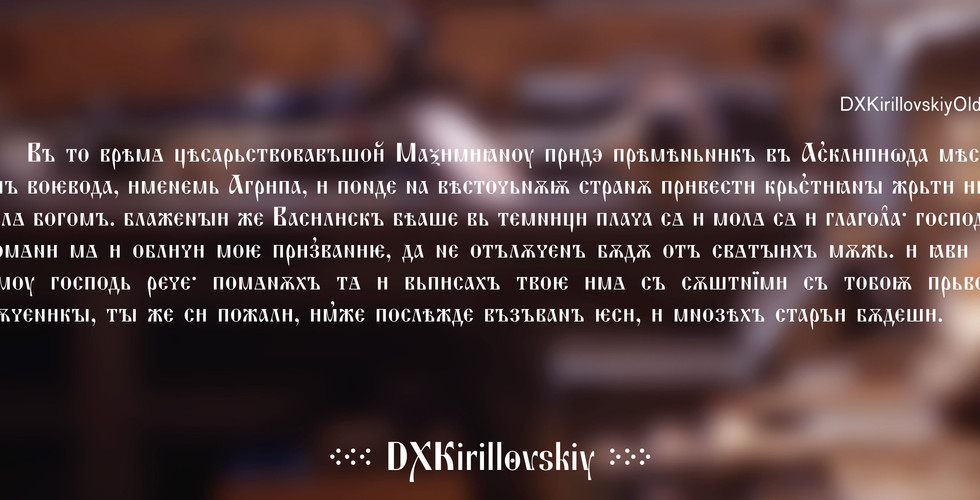
Шрифт Кирилловский/DXKirillovskiy4 авг. 2016 г.1 мин. чтенияВыпущен шрифт Кирилловский/ DXKirillovskiy. За образцы взяты оттиски шрифта из Каталога словолитни О.О.Гербек и Каталога образцов шрифтов ИАН, 1870 г. #шрифт #дореволюционный #русский #старинный #Гербек #DXKirillovskiy #Кирилловский